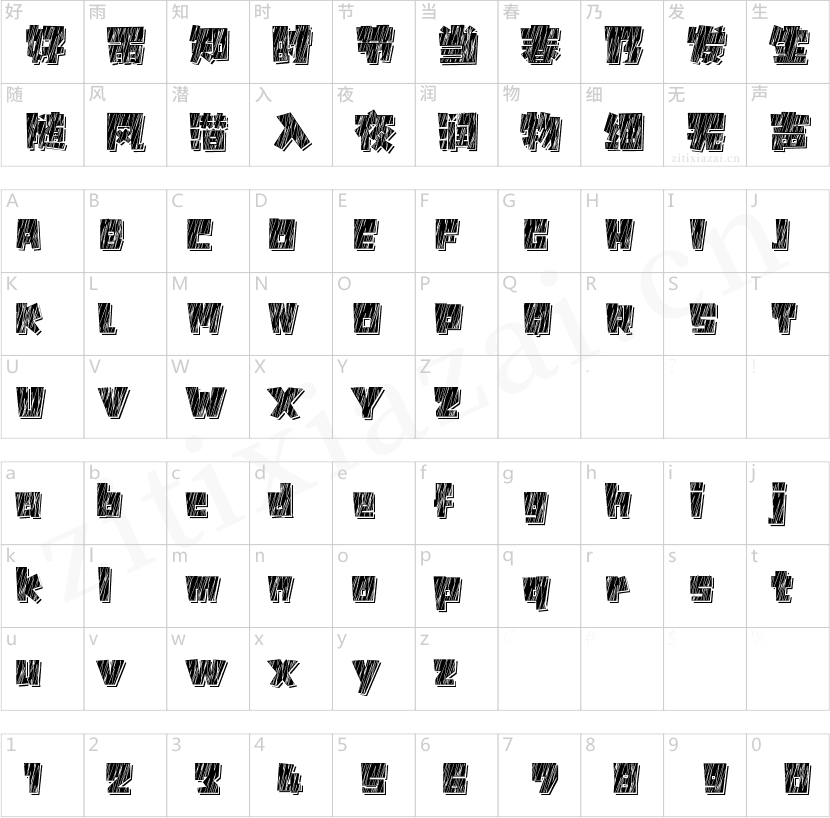
字魂192号-萌趣蜡笔体
字魂字体字小魂萌趣蜡笔体字体是由字魂创意字库设计并生产的一款可商用的字体,被收录于字小魂系列。该字体支持GB-2312标准,包含6765个中文、字母、符号和数字,字体类型偏向创意字体,具有力量、活泼、动漫、可爱、简约、时尚的风格,在市面上广泛用于电商、广告电商、游戏动漫等场景。